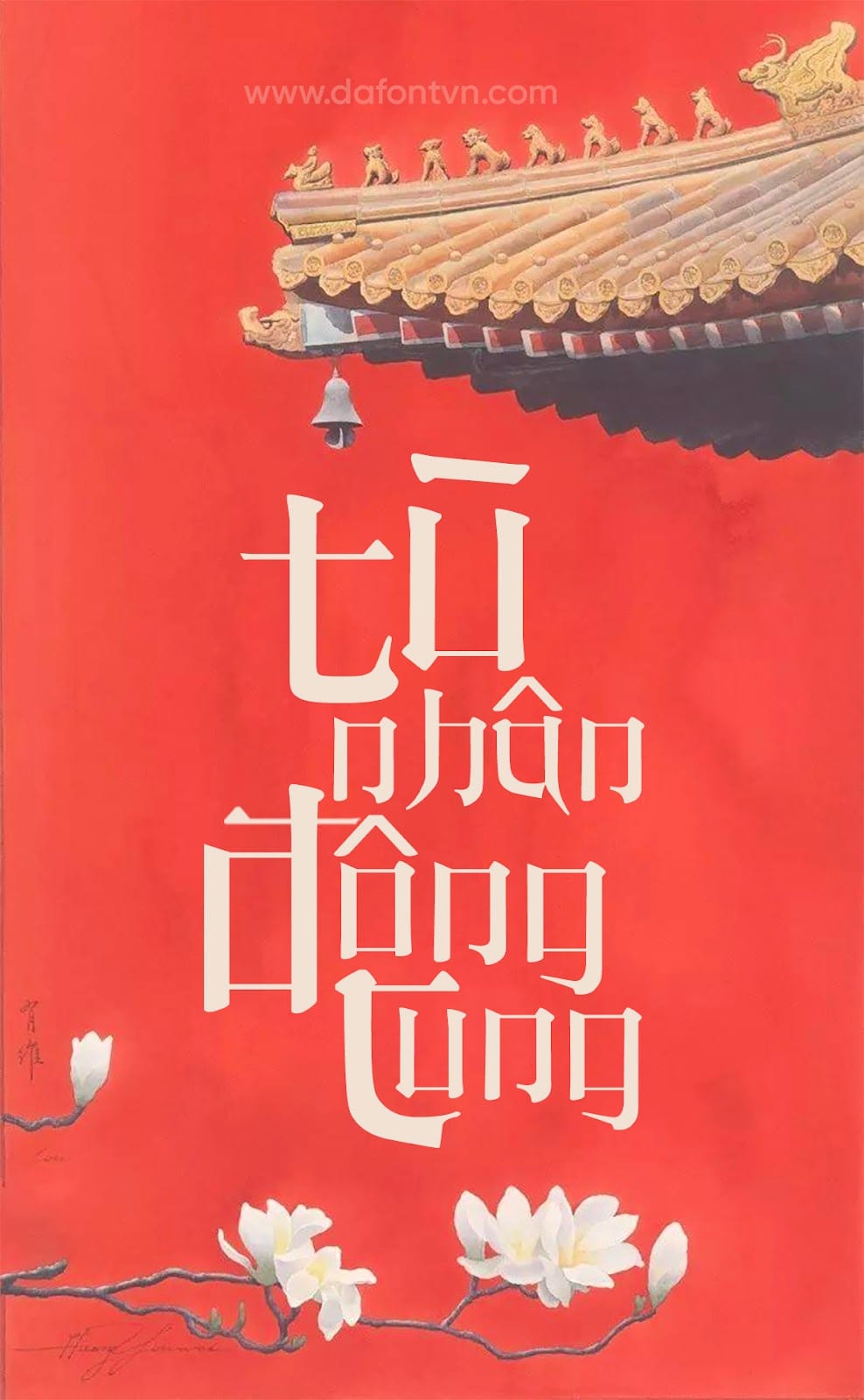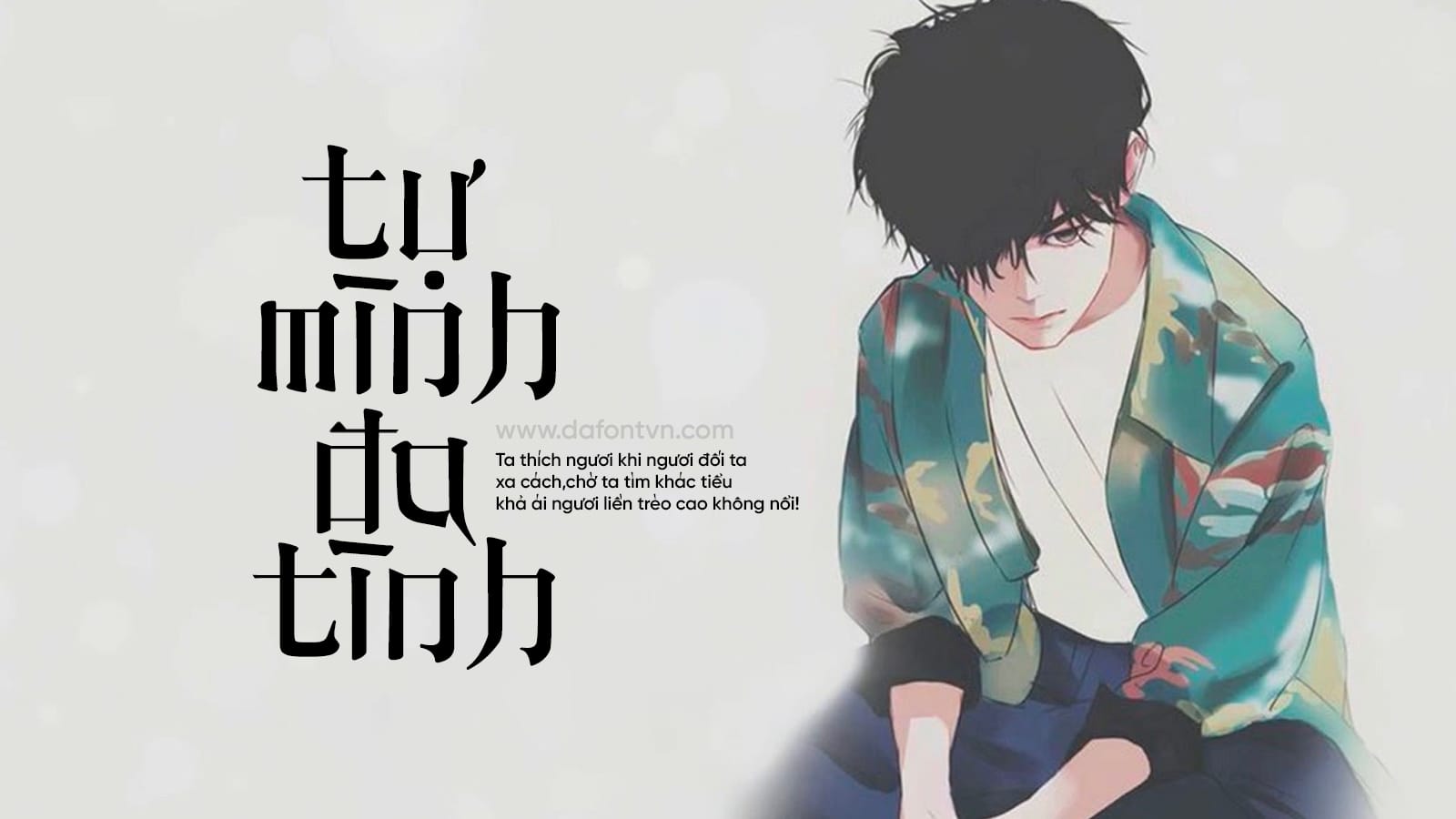
Line Phone là một font chữ dựa theo các nét chữ của chữ Trung Quốc với mỗi chữ cái được tác giả thiết kế theo đặc điểm các nét chữ Trung Quốc. Font Line Phone Việt Hóa đầy đủ và font này dạng như một font thư pháp khá phù hợp dành cho các thiết kế cổ trang. Việt hóa bởi LNTH